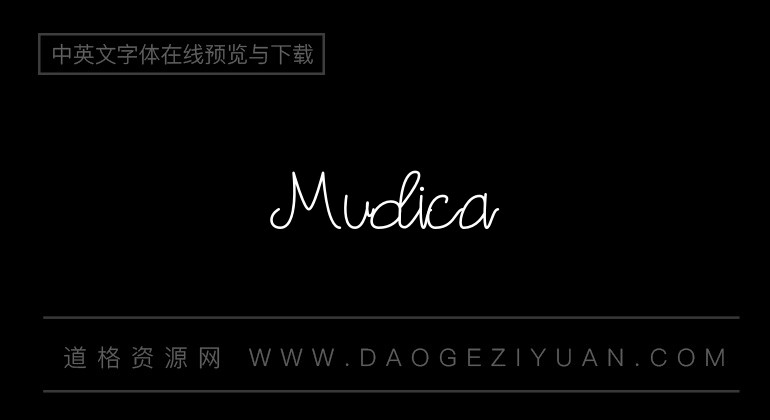
Mudica 是一款现代感十足的英文字体,由著名设计师 David Berlow 于 2018 年设计,它是一款经典的多功能英文字体,适用于品牌标识、标题和文本等。Mudica 的特点是拥有细节丰富的字体,可以满足多种不同的设计需求,同时具有良好的可读性和可视性。它的线条精细,结构紧凑,具有良好的空间感,可以提供清晰、精确的文字表现。内容介绍
Mudica是一款非常不错的手写艺术字体,具有很好的视觉感,适合于文化类的宣传设计、商业类品牌的广告和产品包装设计以及个性化文字排版等较多场景。